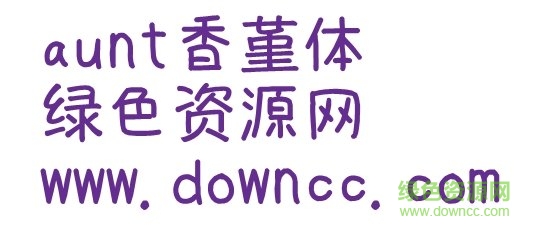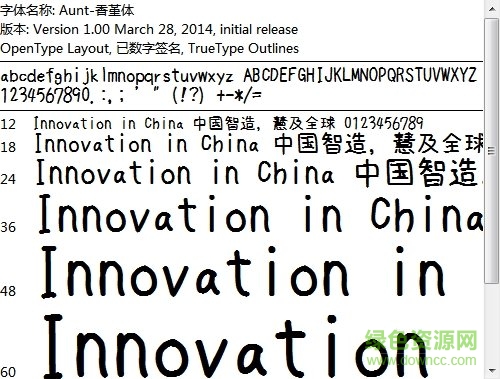
香堇體是aunt系列最活潑清新的一款字體,也叫一品香堇體,筆畫干凈整齊,給人舒適純粹的閱讀好感,沒有多余的點綴,畫風更加清爽得體,喜歡就來綠色資源網(wǎng)免費體驗吧!
一品香堇體是一款手寫風格的卡通字體,字體略帶稚氣,非常具有趣味性,尤其是設計完成之后的整體效果更是出眾,可廣泛應用于平面設計、廣告設計、報紙雜志、正文標題等領域!
一品香堇體字形大方得體,呈卡通風格,整體效果十分出眾,是一款應用于平面設計方面的簡體中文字體!